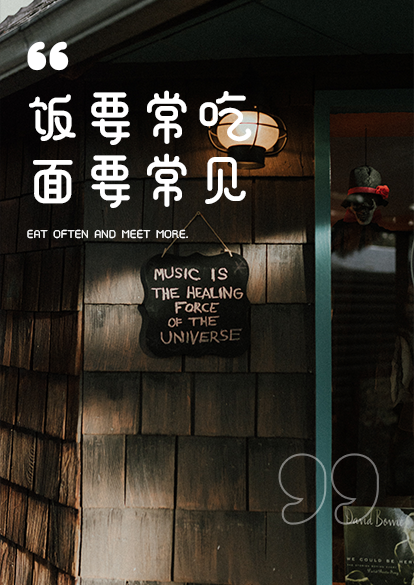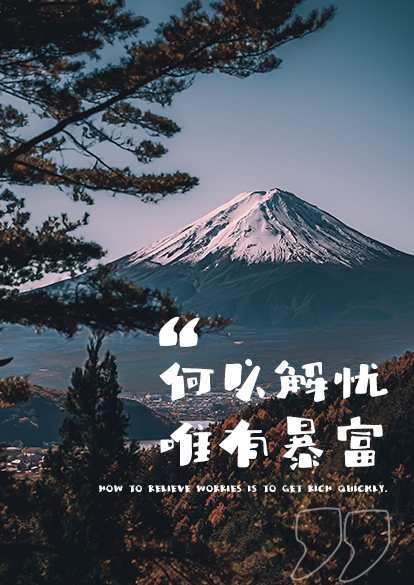
文艺字体有多好用?超文艺清新的情绪类字库推荐
是不是对中规中矩的字体有些审美疲劳?视觉需要缓冲,情绪需要表达,而心情呢,也需要表达。
今天给大家推荐一个情绪类字库——字恋狂,情绪与氛围类字库。匠心独运的设计自成一格,灵动奇特,营造独一无二的氛围感,打破一成不变,临摹内心轮廓,用热烈的笔画勾起身体中跃动的因子,纵情释放!
字恋狂特别黑简
不规整的手写创意字体,横竖粗细形成强烈对比,给人视觉上的冲击,个性张扬。
字型可爱,在笔画两端和转折的地方加上了圆角处理,使其圆润,笔画圆头圆尾,富有独特的亲和力。